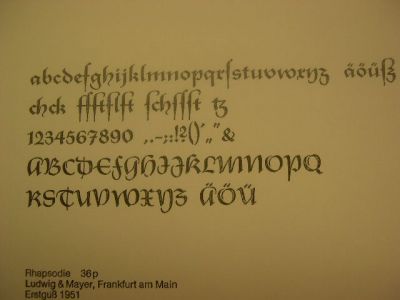
Und bist sicher in der Lage, so in etwa vorzugeben, was aufgedruckt werden soll und in welcher (zur Verfügung stehenden) Bleisatz-Schrift? Und gehst freiwillig auf quadratische Bierdeckel mit abgerundeten Ecken? Verzichtest also auf Rundsatz für runde Bierdeckel?
Ich erkundige mich da mal, was passt.
Das könnte ich mir sehr gut vorstellen ... Futura.
Dein Beispiel ist schön, für jemand in deinem reifen Alter wäre sowas sicher angebracht. Erinnert mich sehr an Eiche rustikal :D.
Spass. Die Rhapsodie is zu "blumig", passt nicht.
Joh..